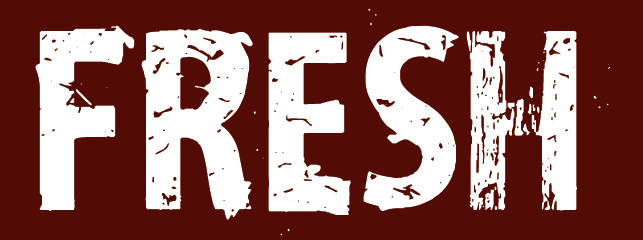
Welche Schrift ist die Originale?
habe hier einen Freefont. VTKS Distress
Welche Schriftart könnte die Originale sein. Ich dachte es könnte die Fago sein, aber das "S" passt schon nicht.